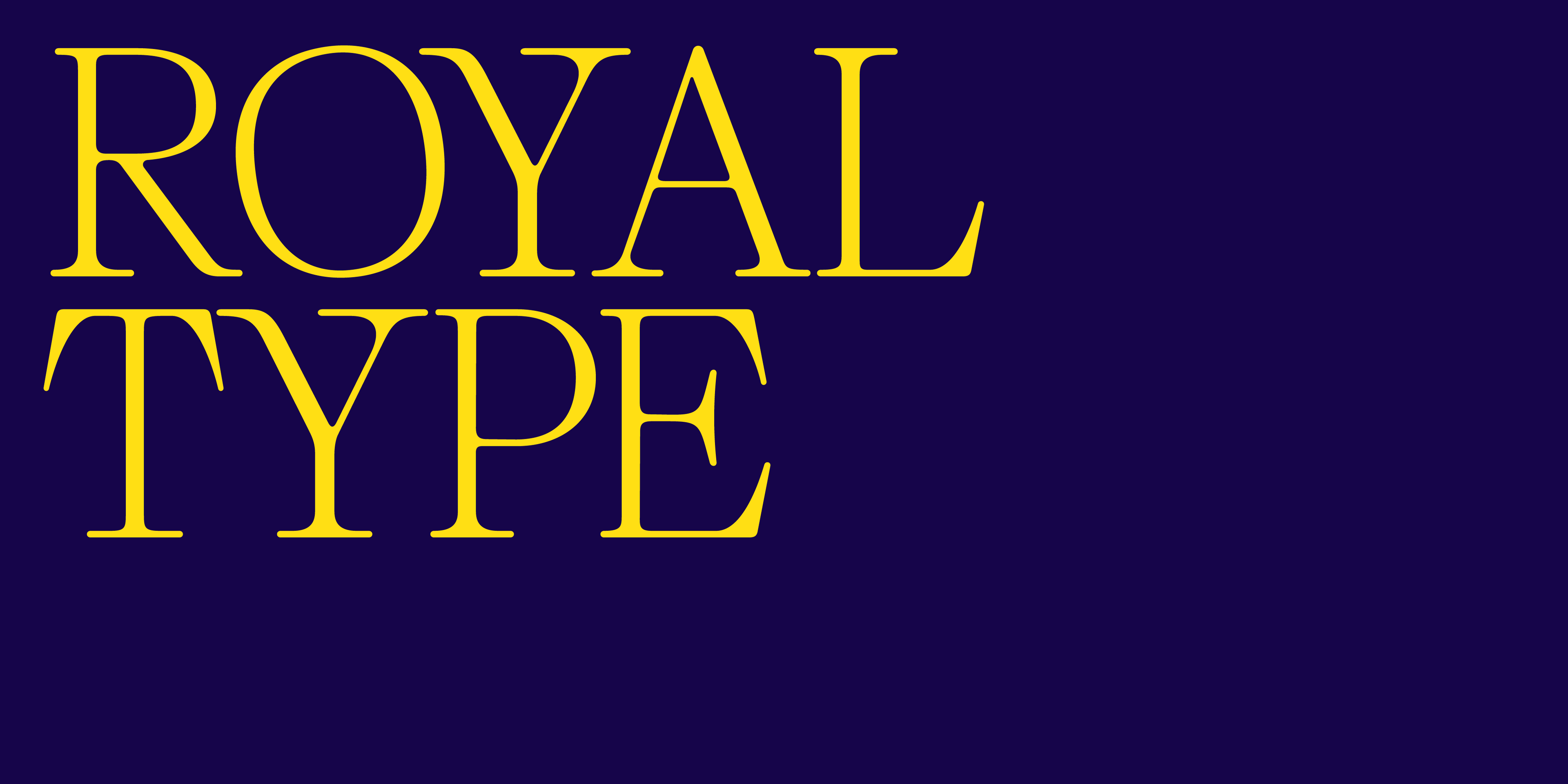
Verwenden Sie königliche Schriftarten, um Ihren Designs einen Hauch von Eleganz und Raffinesse zu verleihen. Egal, ob Sie nach Serifen- oder serifenlosen Schriftarten suchen oder einfach nur einen allgemein königlichen Look erzielen möchten, sehen Sie sich die folgende Schriftartensammlung an. Jede ausgewählte Schriftart verfügt über ein Vorschaubild der wichtigsten Glyphen und enthält eine Erklärung, was das Schriftdesign aussagt und wie man es am besten verwendet.
Klassische Serifenschriften für Überschriften, Bücher und Filmtitel
Bauhaus Mod ist eine klassische Serifenschrift mit einem insgesamt modernen Erscheinungsbild. Die Punzen der Schriftart, wie etwa die Buchstaben e und g, sind weit geöffnet und verleihen ihr einen freundlichen, beliebten Ton. Die Serifen von Mod sind elegant und die Kugelenden sind schlank und abgerundet. Diese Schriftart ist vielseitig und funktioniert sowohl in Großbuchstaben als auch in normaler Schreibweise gut.
Quil sieht weniger feminin aus, wenn man nur die Serifen betrachtet – sie sind scharf und robust, aber elegant. Einige Buchstaben wie B und R fallen jedoch auf, indem sie dort, wo sie normalerweise mit ihren Stämmen verbunden sind, einen gebogenen Strich aufweisen. Diese Schriftart ist schön und einzigartig und sieht besonders edel aus, wenn sie in dünneren Schriftstärken verwendet wird.
Zoomen Sie auf diese Schriftart. Sie heißt Kijs und ist wunderschön in ihren Details. Elegante Endkurven, abgerundete Gabelungen und einige kursive Buchstaben verleihen dieser Schriftart ein natürliches, aber königlich wirkendes Design. Weitere Informationen zu Kijs Black .
Schicke Sans-Serif-Schriften für Einladungen und Überschriften
Bauhaus Chez ist eine kontrastreiche Schriftart mit hellen und kräftigen Buchstabenstrichen. Die oberen Striche sind auf einer Seite abgerundet, was einen beliebten und eleganten Stil erzeugt. Chez wird mit Stilsätzen (alternative Buchstaben) geliefert, beispielsweise den Buchstaben A und E, die Sie austauschen können, um einzigartige Logos und individuelle Überschriften zu erstellen.
Roma ist eine weitere Kontrastschriftart für einen königlichen Touch, jedoch mit einem etwas minimalistischeren Design. Die Standardbuchstaben sind gerade, aber die Schriftart bietet viele alternative Buchstaben, die Sie austauschen können, um ein runderes Gefühl zu erzeugen, indem Sie beispielsweise die Buchstaben a, d und w verwenden. Weitere Designvarianten finden Sie auf der Roma-Detailseite .
Diese Schriftart aus den 1920ern ist Teil der Art-Deco-Kollektion . Sie hat Groß- und Kleinbuchstaben, funktioniert aber am besten in Großbuchstaben – einfach, weil dieser Schreibstil damals beliebt war. Wie bei klassischen Schriftarten aus den 20ern befinden sich die Querbalken von Quin nicht in ihrer optischen Mitte; sie sind höher oder tiefer positioniert. Vergleichen Sie die Buchstaben A und E. Die C-Schale der Schriftart ist näher an ihrer vertikalen Mitte abgeschnitten. Wir können auch den typischen, erhöhten Kontrast zwischen schmalen und breiten Buchstabenformen erkennen, z. B. E und O. All diese Designmerkmale machen dies zu einem Art-Deco-Schriftdesign.
Für ein noch königlicheres Gefühl kombinieren Sie diese Schriftart mit einer königlichen Farbpalette aus Kastanienbraun, Violett und Dunkelblau in Kombination mit Gold oder Gelb. Weitere Designdetails finden Sie auf Quin .
Moderne, abgerundete Schriftarten – von ausgefallen bis auffällig
Kijs Thin gehört zur selben Schriftfamilie wie die schwarze Version weiter oben auf dieser Liste. Einige der Buchstaben sind keine typischen Serifenzeichen – sie sind eine moderne Version in Handschriftform, was dieser Schriftart ein cooles Aussehen verleiht. Durch Zugriff auf die Stilsätze können Sie die Standardbuchstaben durch normale Serifenzeichen ersetzen.
Soft Display ist eine freundliche Serifenschrift mit geselligem Designcharakter. Die Buchstaben sind relativ breit, die Punzen sind offen und manchmal geneigt und die Buchstabenstiele sind auf einer Oberseite abgerundet – all diese Merkmale tragen zu einem insgesamt geometrischen, räumlichen Aussehen bei. Diese Schriftart ist elegant, wenn Sie ein helleres, großgeschriebenes Textdesign verwenden.
Eine lustige Schriftart, die mit der Vorstellung von Königlichkeit kollidiert, ist Lace Rounded , ein moderner Handschriftstil, mit dem Sie beispielsweise Zuckergusstext auf Hochzeitstortengrafiken imitieren können.